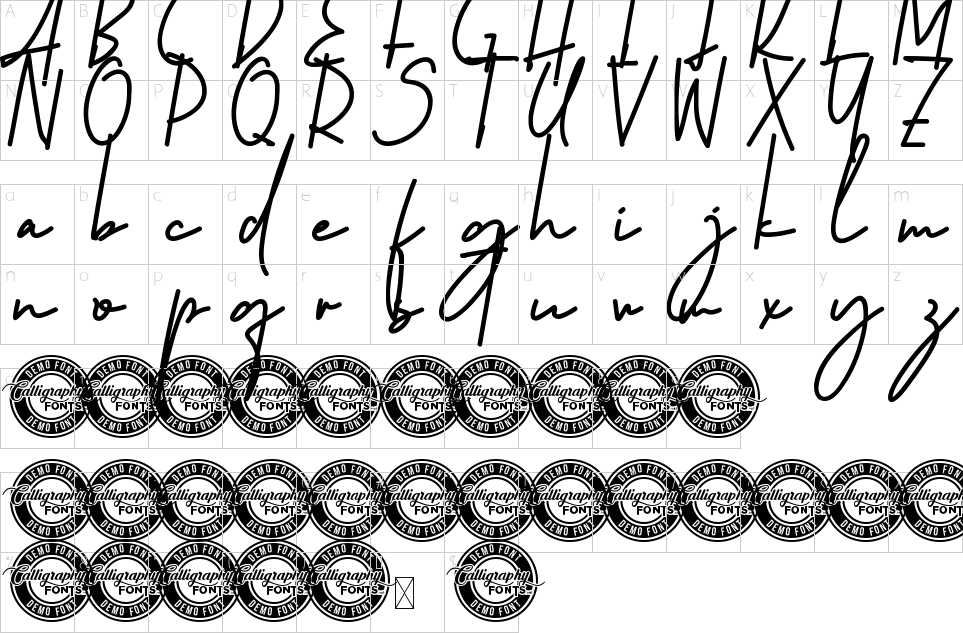
Descubra a beleza e versatilidade do Great Life Font para seu próximo projeto gráfico com esta fonte gratuita. Desenvolvida pela incrível equipe da CalligraphyFonts, essa font oferece uma mistura única de elegância e simplicidade que certamente irá enriquecer sua composição de texto. Com 1001 opções disponíveis no catálogo de Free Fonts da Cloud, você não precisa gastar nada para experimentar o Great Life Font. Desenvolvida para os designers de todo mundo, essa font é fácil de usar e oferece uma variedade impressionante de formatos, desde Windows até Mac. Seja para criar um layout profissional ou simplesmente adicionar um toque criativo a sua próxima produção gráfica, o Great Life Font está aqui para ajudar. Se você está buscando uma fonte bonita que não comprometa seu orçamento, essa é definitivamente uma opção a considerar. Descubra agora mesmo como a Great Life Font pode enriquecer sua arte digital e experimente suas 1001 possibilidades gratuitas!